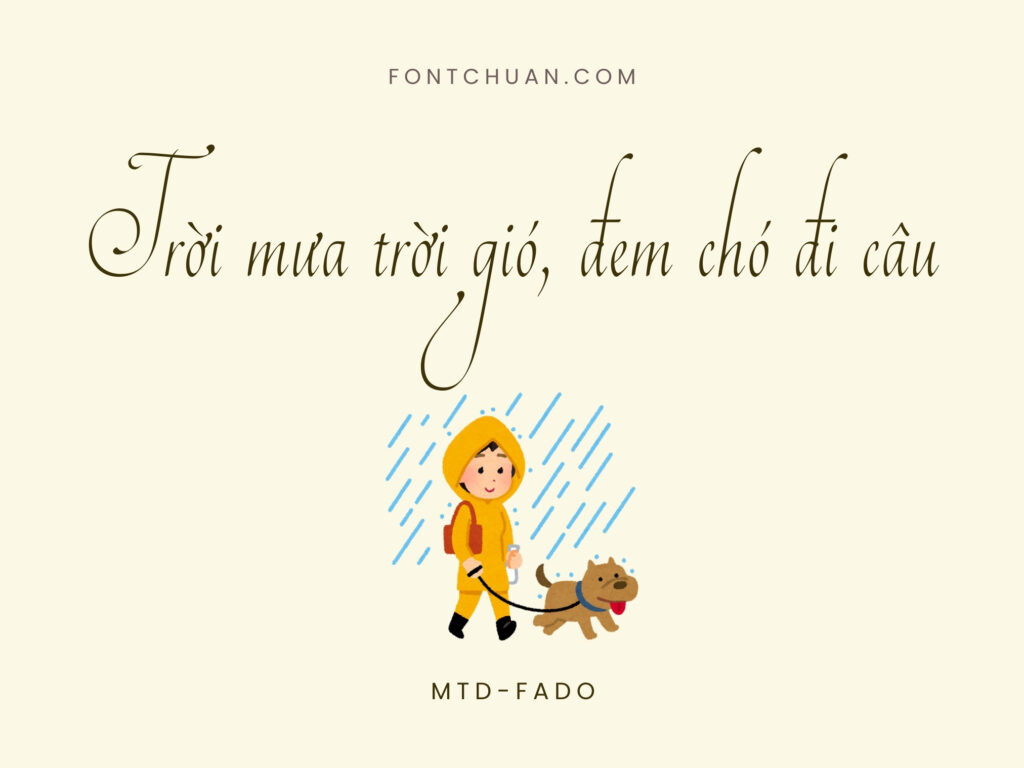
Font MTD Fado Việt Hóa
Tác giả Font: Olga Umpeleva
Font MTD Fado là một phông chữ script hiện đại, được thiết kế bởi Olga Umpeleva và đã được Việt hóa bởi Mộc Hạ, hỗ trợ tiếng Việt cùng hơn 90 ngôn ngữ khác. Font này nổi bật với các đường nét mềm mại và uyển chuyển, mang đến cảm giác thân thiện và gần gũi. Đây là một trong những phông chữ được cộng đồng thiết kế đánh giá cao và ứng dụng trong nhiều dự án sáng tạo.
MTD Fado rất phù hợp cho các thiết kế logo, thương hiệu cá nhân, thiệp mời, tiêu đề, bao bì sản phẩm và các ấn phẩm yêu cầu sự tinh tế và cá nhân hóa. Các ngành nghề phù hợp bao gồm quảng cáo, giáo dục, công nghệ, thiệp cưới và ảnh cưới. Font này cũng lý tưởng cho các sự kiện như Tết, Giáng sinh, Valentine và các lễ hội khác.